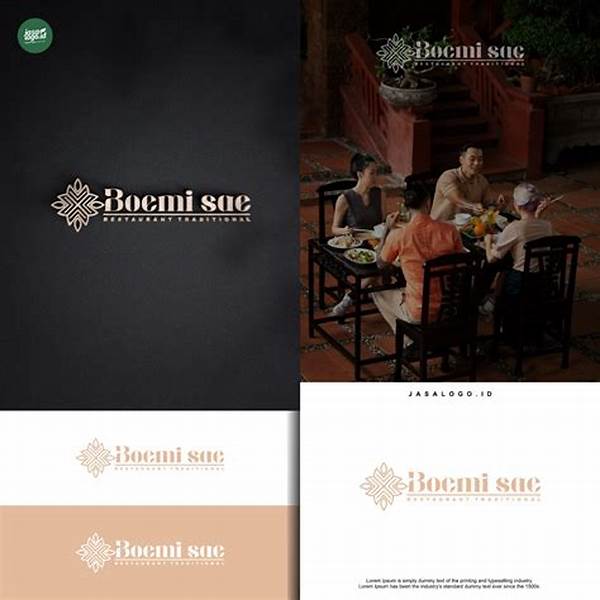
Halo, teman-teman desainer! Kali ini kita akan membahas sesuatu yang mungkin bikin kamu penasaran: strategi font dalam desain logo. Desain logo bukan hanya tentang gambar atau simbol. Font yang kamu pilih buat logo juga bisa membawa dampak besar. Pikirkan saja, dengan font yang tepat, logo bisa jadi lebih berkesan dan langsung nempel di ingatan orang. Yuk, kita gali lebih dalam soal ini!
Memahami Peran Font dalam Desain Logo
Font dalam desain logo punya peranan yang nggak kalah penting dari elemen lainnya. Bayangkan saja, sebuah logo bisa terlihat profesional atau playful hanya dengan mengganti jenis font. Ngobrol soal ini, strategi font dalam desain logo kadang menjadi penentu apakah pesan dari brand bisa tersampaikan atau nggak. Sama seperti fashion, memilih font yang tepat bisa mencerminkan kepribadian sebuah brand.
Para desainer sering kali memilih font yang berani untuk brand yang ingin membangun kesan kuat, tetapi lama dikenal. Di sisi lain, beberapa font yang halus dan elegan dipilih untuk merepresentasikan brand yang lebih tenang dan profesional. Misalnya, brand fashion mewah sering menggunakan font serif, sementara perusahaan teknologi lebih sering memilih sans-serif untuk tampilan modern dan fresh.
Penggunakan strategi font dalam desain logo bisa jadi cukup rumit jika kamu nggak tahu ke mana harus mengarahkan pilihanmu. Karena itu, penting banget buat memahami karakteristik dari setiap jenis font dan bagaimana mereka mampu memperkuat atau malah mengaburkan pesan brand kamu. Jangan asal pilih ya!
Elemen Penting dalam Memilih Font
1. Kepribadian Merek
Memilih font harus sesuai dengan kepribadian merek. Strategi font dalam desain logo ini memastikan font yang dipilih memperkuat dan mencerminkan nilai brand.
2. Baca dan Jelas
Pastikan font yang dipilih mudah dibaca dalam berbagai ukuran, dari spanduk besar hingga kartu nama kecil. Jangan abaikan kenyamanan membaca!
3. Kesesuaian dengan Elemen Lain
Font harus bersinergi dengan warna, ikon, dan elemen desain lainnya dalam logo. Semua elemen harus terasa satu kesatuan.
4. Unik dan Berbeda
Usahakan memilih font yang unik agar logo mudah diingat. Font yang sama dari kompetitor bisa bikin brand kita jadi nggak stand out.
5. Fleksibilitas
Font harus fleksibel untuk digunakan di berbagai platform dan media. Ini bagian dari strategi font dalam desain logo agar logo tetap tampil konsisten.
Membangun Identitas dengan Font yang Tepat
Mari kita bahas lebih lanjut kenapa pemilihan font itu bisa membangun identitas sebuah brand. Ketika melihat atau membaca suatu logo, secara nggak langsung, otak kita menilai kepribadian dari brand tersebut. Misalnya, font script yang elegan bisa memberi kesan premium, sedangkan font geometris dan tegas bisa memberi kesan modern dan inovatif. Jadi, strategi font dalam desain logo tidak boleh dianggap remeh.
Brand dengan target audiens yang muda mungkin lebih suka font sans-serif yang simpel dan segar. Sementara itu, brand yang menyasar audiens yang lebih luas dan beragam mungkin akan memilih font yang netral tapi tetap memiliki karakter yang ‘nendang’. Dengan begitu, strategi ini membantu brand kamu lebih dikenal dan diingat di antara banyaknya pesaing.
Pertimbangan Teknis dalam Memilih Font
Memahami aspek teknis dari font juga penting. Di sinilah strategi font dalam desain logo menjadi sangat teknis. Jangan lupa untuk selalu memperhatikan rasio dan ukuran huruf saat diaplikasikan ke berbagai media, biar tetap terbaca dengan jelas.
1. Kerning dan Spacing
2. Desain Scalable
3. Kontras Warna dengan Latar
4. Penggunaan Font Kustom
5. File Format yang Tepat
6. Kesesuaian dengan Branding
7. Aksesibilitas Font
8. Tes di Berbagai Platform
9. Legalitas Penggunaan Font
10. Konsistensi dalam Penggunaan
Menyampaikan Pesan dengan Font yang Tepat
Strategi font dalam desain logo sangat berpengaruh dalam menyampaikan pesan brand. Meskipun kadang nggak disadari oleh konsumen, font punya daya tarik tersembunyi dalam mengomunikasikan pesan brand secara emosional. Contohnya, font yang kokoh dan berstruktur bisa memberi perasaan aman dan kokoh kepada audiens.
Seiring semakin berkembangnya teknologi, hacking strategi font dalam desain logo bisa dilakukan dengan lebih kreatif. Komputer dan software desain saat ini menawarkan lebih banyak pilihan font yang bisa dieksplorasi untuk memenuhi kebutuhan estetika dan teknis. Jadi, jangan terburu-buru ketika memilih font untuk logo kamu. Pastikan kamu memberi ruang bagi kreativitas dan juga ketepatan!
Kesimpulan tentang Strategi Font dalam Desain Logo
Gimana, makin banyak pertimbangan kan dalam memilih font? Strategi font dalam desain logo memang bisa jadi pembeda antara brand satu dengan yang lain. Semua elemen harus bekerja sama demi mencapai tujuan branding yang efektif. Pemilihan font yang salah bisa mendatangkan kesan tidak profesional. Jadi, perlu tingkatkan pemahaman tentang font.
Pengalaman dan referensi juga sangat berpengaruh pada keberhasilan strategi font dalam desain logo. Nah, perlahan tapi pasti, berlatihlah untuk menjadi seorang desainer yang peka terhadap detail. Semakin sering bereksperimen dengan berbagai font dan penggunaannya akan memberi kamu insight lebih dalam lagi. Dengan begitu, logo bukan hanya sekadar gambar, tapi media komunikasi yang kuat antara brand dan konsumen.